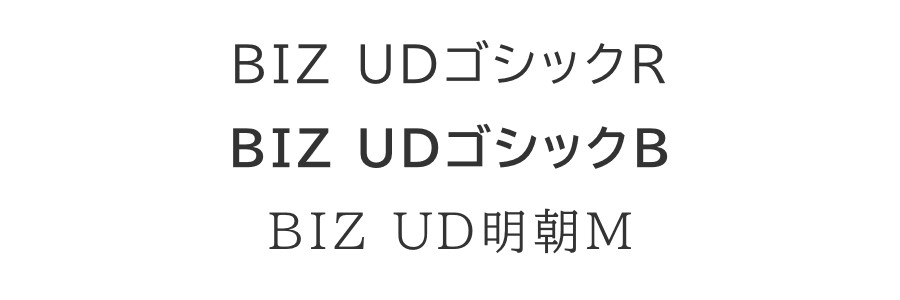
- ビジネス文書作成向けUDフォントソリューション「MORISAWA BIZ+(モリサワ ビズプラス)」
ビジネス文書作成向けUDフォントソリューション「MORISAWA BIZ+(モリサワ ビズプラス)」
「MORISAWA BIZ+」は、ビジネスシーンのドキュメントやコンテンツの作成にUDフォント(ユニバーサルデザインフォント)の利用を提案する新しいサービス。
読みやすさのエビデンスがあり、商業印刷をはじめ幅広く使用されているモリサワのUDフォント 43書体を、Word、Excel、PowerPointでも使いやすい仕様で提供。
報告書やプレゼンテーション資料、掲示物など幅広くご利用いただけるベーシックな明朝体とゴシック体、グラフや表組みなど小さなスペースに最適なコンデンス書体、優しい雰囲気の丸ゴシック体、学習教材や丁寧に伝えたいコンテンツに有効な教科書体を取り揃え、より伝わりやすい文書作成をサポートする。
「MORISAWA BIZ+」を10月24日から販売
モリサワは、ビジネス文書作成向けUDフォントソリューション「MORISAWA BIZ+(モリサワ ビズプラス)」の販売を2018年10月24日より開始することを発表した。
「MORISAWA BIZ+」は、ビジネスシーンのあらゆるドキュメントやコンテンツの作成に、ユニバーサルデザイン(UD)フォントの利用を提案するサービス。
読みやすさのエビデンスがあり、商業印刷をはじめ幅広く使用されているモリサワのUDフォントを、Word、Excel、PowerPointでも使いやすい仕様で提供する。
▼書体ラインナップ
BIZ UD新ゴ
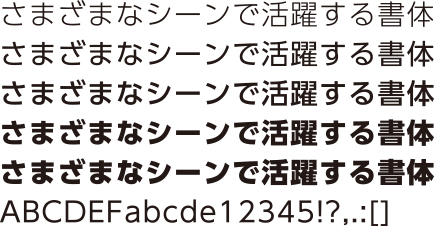
ウエイト:Light/Regular/Medium/Bold/Heavy(上から)
報告書や送付案内などの書類からサインやプレゼンテーションなど幅広く使える、遠くからもはっきりと見やすいゴシック体。
BIZ UD黎ミン
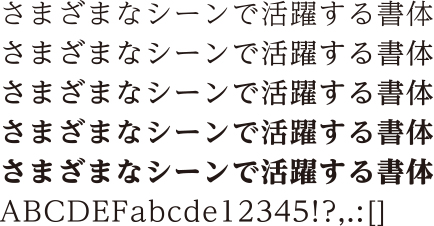
ウエイト:Light/Regular/Medium/Bold/Heavy(上から)
報告書や通知書などのあらたまった文書にも使いやすく、縦組み・横組みのいずれも読みやすい明朝体。
BIZ UD新ゴ C60
ウエイト:Light/Regular/Medium/Bold/Heavy(上から)
表組みなど限られたスペースに多くの情報を入れる際に活躍する長体のゴシック体。
BIZ UD新ゴ C80
ウエイト:Light/Regular/Medium/Bold/Heavy(上から)
表組みなど限られたスペースに多くの情報を入れる際に活躍する長体のゴシック体。
BIZ UD新丸ゴ
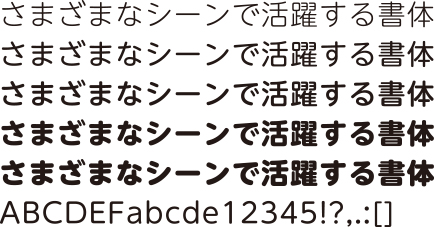
ウエイト:Light/Regular/Medium/Bold/Heavy(上から)
お知らせやご案内など親しみやすい印象にしたい文書に最適な、すっきりと明快な丸ゴシック体。
UD デジタル 教科書体 N
ウエイト:Regular/Medium/Bold/Heavy(上から)
学習電子黒板の表示や、子どもたちの学びに合わせた教材作成などに最適なUD対応の教科書体。
UD Digikyo Latin
ウエイト:Regular/Medium/Bold/Heavy(上から)
UDデジタル教科書体欧文の正体。文部科学省の小学英語新教材の欧文形状に準じた、初めて英語学習に取り組む子どもたちにも読みやすい欧文書体。
UD Digikyo Italic
ウエイト:Regular/Medium/Bold/Heavy(上から)
UDデジタル教科書体欧文のイタリック体。文部科学省の小学英語新教材の欧文形状に準じた、初めて英語学習に取り組む子どもたちにも読みやすい欧文書体。
UD Digikyo Writing
ウエイト:Regular
UDデジタル教科書体の書き学習用欧文書体。文部科学省の小学英語新教材の欧文形状に準じ、大文字の書き学習にも考慮した4線比率の欧文書体。
UD Digikyo Kigo
ウエイト:r/m(上から)
UDデジタル教科書体の学習記号。算数・理科の学習に必要な単位記号などを揃え、算数問題や模範解答、ノートの取り方指導の教材制作などに活用できる記号書体。
Windows10ユーザーなら無料で使用できるBIZ UDフォント「BIZ UDゴシック」
本文からサインまで、さまざまな用途に対応できるMORISAWA BIZ+無償版に収録されているゴシック体。
ウエイト Regular/Bold(上から)
Windows10ユーザーなら無料で使用できるBIZ UDフォント「BIZ UD明朝」
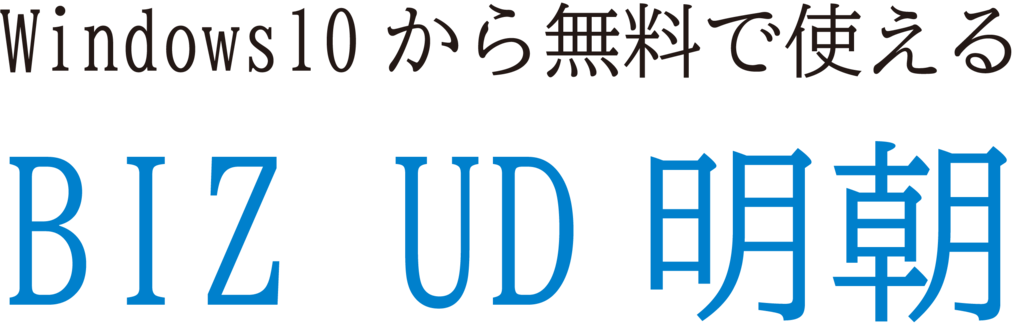
書類の本文をはじめ、さまざまな用途に対応できるMORISAWA BIZ+無償版に収録されている明朝体。
ウエイト:Medium
モリサワのビジネス文書向けUDフォントソリューション「MORISAWA BIZ+」が2018年度グッドデザイン賞を受賞
モリサワのビジネス文書作成向けUDフォントソリューション「MORISAWA BIZ+(モリサワ ビズプラス)」が、2018年度グッドデザイン賞を受賞した事が2018年10月3日に発表された。
「MORISAWA BIZ+」は、ビジネスシーンのあらゆるドキュメントやコンテンツの作成に、ユニバーサルデザイン(UD)フォントの利用を提案する新しいサービス。
企業や自治体など多くのユーザーにより品質の高い書類作成を促す画期的なサービスである点やサービスの普及により日本全体の情報伝達の品質向上が期待できる点が評価された事が受賞の要因とのこと。
MORISAWA BIZ+がIAUDアウォード2017銀賞を受賞
「MORISAWA BIZ+(モリサワ ビズプラス)」が、一般財団法人 国際ユニヴァーサルデザイン協議会が主催する「IAUDアウォード2017」で銀賞を受賞したことを3月15日に発表した。
IAUDアウォード
IAUDアウォードは、民族や文化、慣習、国籍、性別、年齢、能力等の違いによる生活の違いに不便さを感じることなく、 一人でも多くの人が快適で暮らしやすい ユニヴァーサルデザイン(UD)社会の実現に向けて特に顕著な活動の実践や提案を行なっている団体・個人を表彰するアワード。
MORISAWA BIZ+特徴
MORISAWA BIZ+は日常的に作成するビジネス文書にUDフォントが使えるフォントソリューション。
Microsoft Officeでの利用に最適化した「BIZ UDフォント」とBIZ UDフォントがすぐに使える「BIZ UDフォントテンプレート(Word、PowerPoint、Excel用)」「BIZ UDフォントガイド」が提供される。また「BIZ UDゴシック/明朝 スタンダード版」では、ゴシック2書体、明朝1書体の3書体を無償で利用できる他、「BIZ UDフォント アドバンス版」(サブスクリプション方式、価格未定)では、BIZ UD新ゴ、BIZ UD新ゴ コンデンス80と60、BIZ UD黎ミン、BIZ UD新丸ゴの各5ウエイト全25書体が提供される。
2017年10月17日に正式リリースされ、次いでMORISAWA BIZ+特設ページもオープンした。特設ページからはBIZ UDフォントスタンダード版が無償ダウンロードできる。
BIZ UDフォント
Microsoft Officeに最適化した「見やすい」「読みやすい」「間違えにくい」をコンセプトに開発されたユニバーサルデザインフォント。
正確な情報伝達が必須のビジネス文書だからこそ「見やすい」「読みやすい」「間違えにくい」特徴を持つUDフォントを使用することで、数字が「3」なのか「8」なのか読み間違える、濁点と半濁点の判別ができない…、細い文字がかすれて読めない…、そういった文字の不明瞭さでのトラブルを避けることができる。
モリサワが提供するUDフォントは、通常のフォントと比べて可視生・可読性に優位性が認められており、数字の読み間違いを防止する、小さい文字でも読みやすいよう画線の間を大きくとる、濁点・半濁点を区別しやすくするなど、状況による読み間違いを防ぐさまざまな工夫がされており、ビジネス文書との相性が良いというのがリリース理由のようだ。